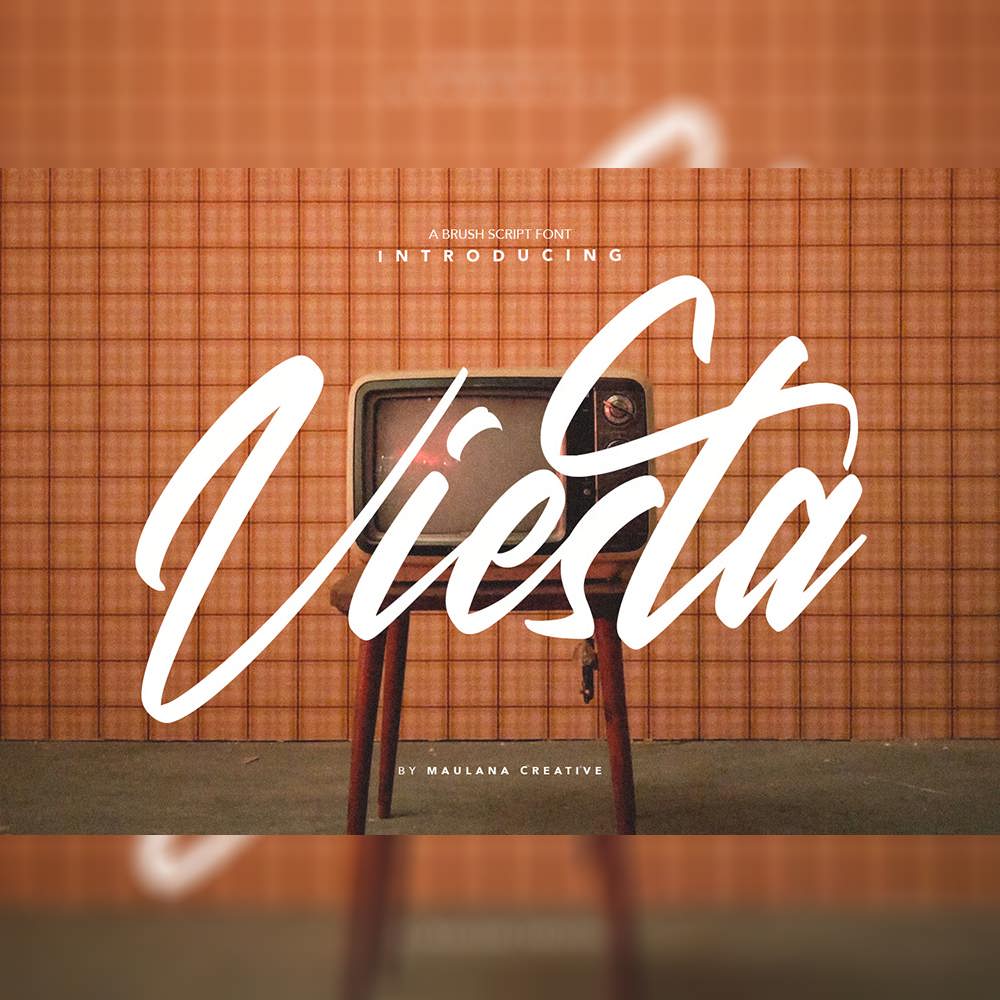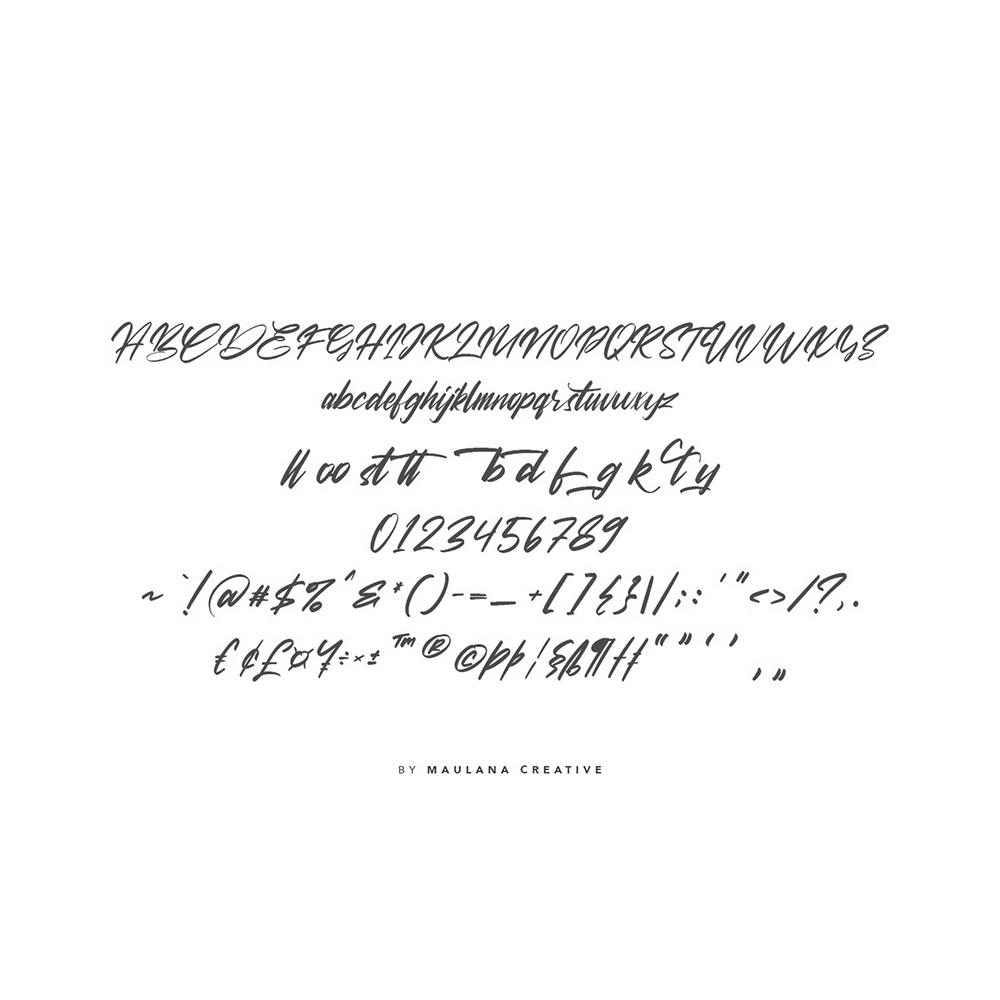
دانلود فونت انگلیسی Viesta Font
با فونت پرمیوم و انگلیسی Viesta Font به طرحهای خود جلوهای اصیل و دستساز ببخشید. فونت دستساز Viesta براش اسکریپت وینتیج و دارای حروف جایگزین برای امضا، لوازم التحریر، لوگو، نقل قولهای تایپوگرافی، جلد مجله یا کتاب، سربرگ وبسایت، پوشاک، برندسازی، طراحی بستهبندی و غیره ایدهآل است.
مزایای استفاده از فونت لاتین Viesta چیست؟